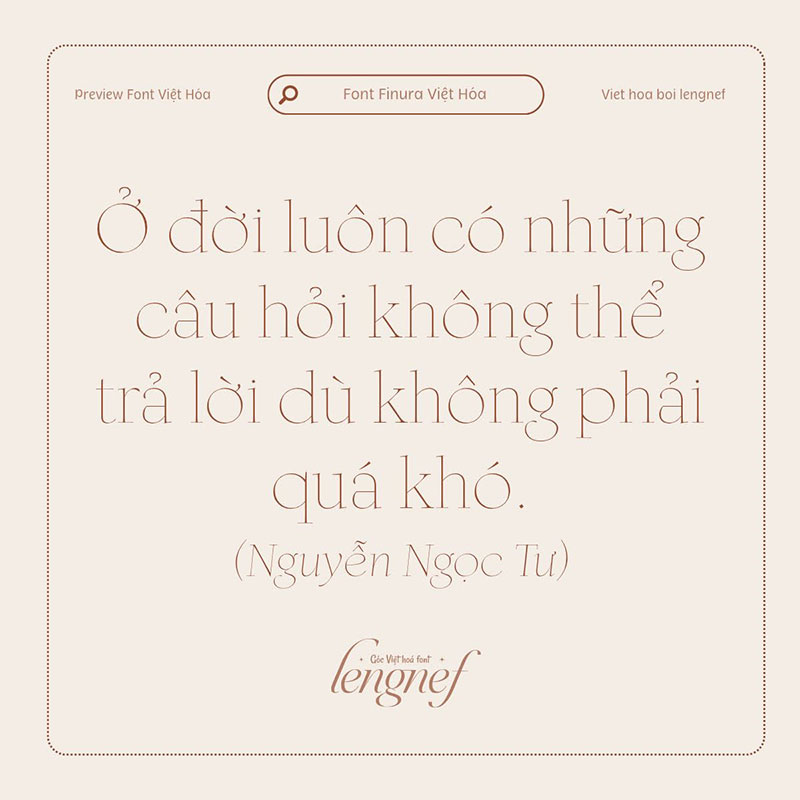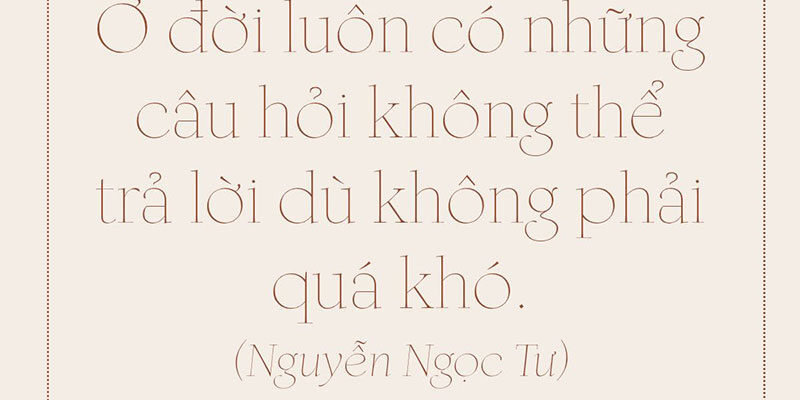
- Tác giả: Dino dos Santos
- Việt hóa: lengnef
Finura thuộc loại font serif được lấy cảm hứng từ kiểu chữ Mỹ những năm 60. Là kiểu chữ rất mảnh và tinh tế, với nhiều chi tiết mang đến sự đơn giản và dễ đọc cho các hình thức cổ điển. Font này Việt hóa 2 bản thường (roman) và nghiêng (italic).